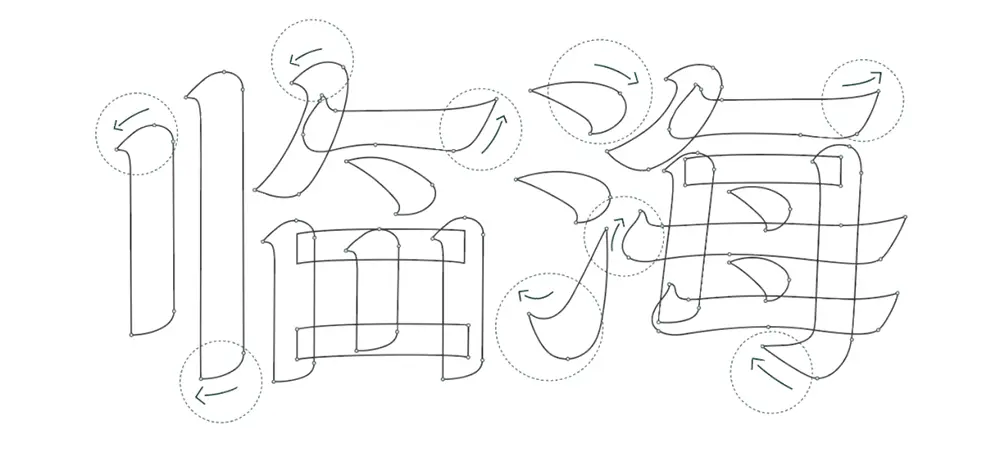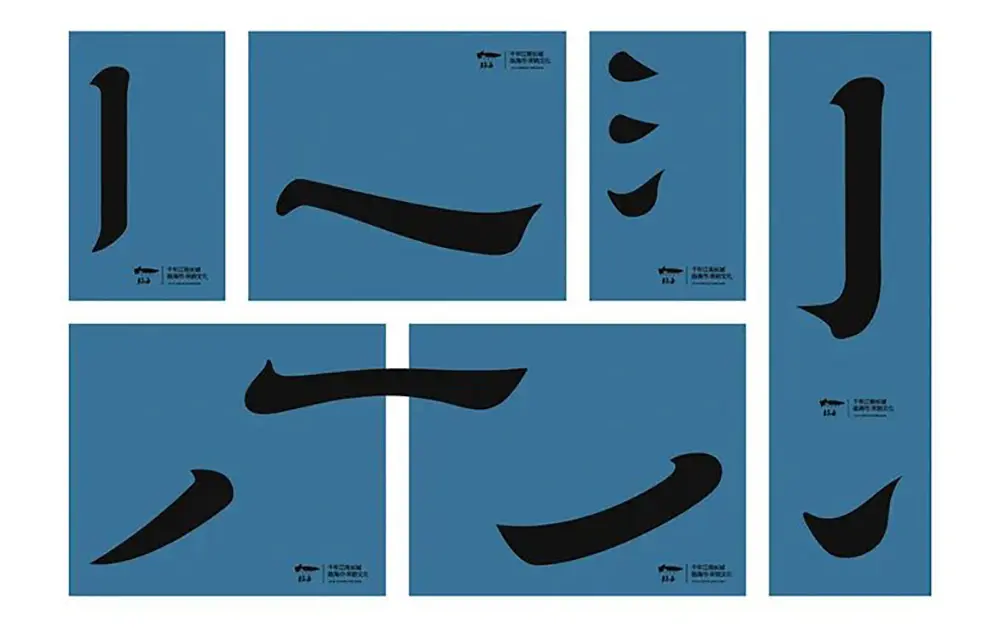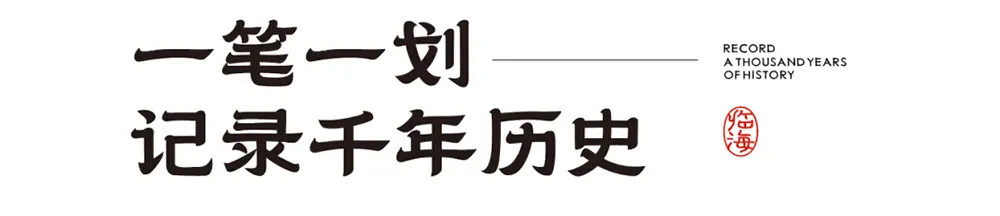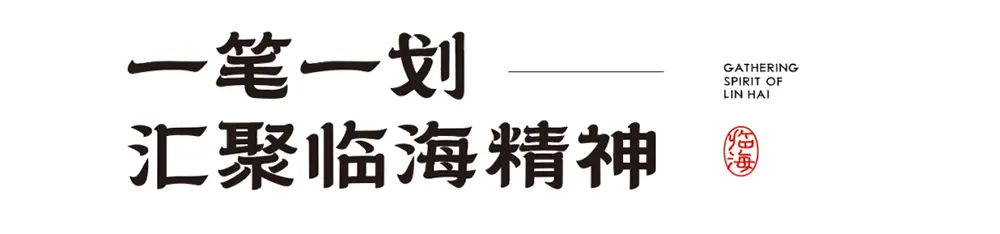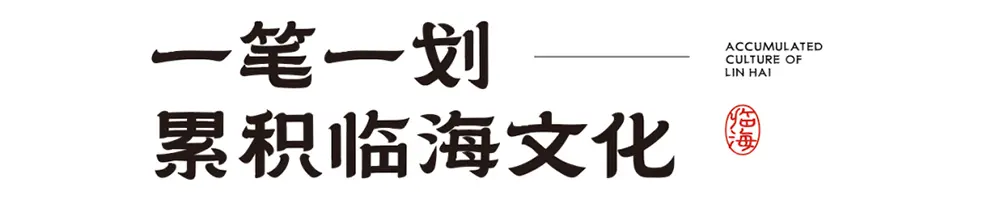
一座城市的影響力取決於城市文化的影響力,經營城市品牌,經營的是一座城市的文化辨識度......,為持續打響“ 千年台州府、江南真宋城 ”文旅品牌形象,讓文化傳播更具辨識度,市社發集團積極謀劃,深度挖掘臨海文化內涵,與鄉立方團隊攜手打造推出了擁有臨海獨特風格和時代烙印的專屬字體。
台州府城牆、龍興寺、千年紫陽街等,文化古蹟星羅棋佈,駱賓王、戚繼光、朱自清等,敘說著臨海文化綿長的故事,文人舞墨,匠者築基,共同鑄就了臨海的文化底蘊,正因如此臨海能較早躋身於“國家歷史文化名城”之列,能有信心對世界說“千年古城,最憶臨海”。
歷史底蘊深厚、文化資源豐富,這是臨海不可複製的獨特稟賦,但如何讓世界認識臨海呢,源浚者流長,根深者葉茂,文字是文化傳承的標誌,臨海字體,更是傳播臨海文化的基礎元素。
一城化一字,一字如一城,站在時光的縱軸上向前望去,隸書的演變史,也是臨海城市變遷的縮影。
將千年古城、人文繁盛、山水之韻,等臨海城市特質,結合漢字五大字體之一的隸書體,隸書,興盛於漢代,也是臨海城市起源的時代,隸書所具有的厚重、古典、拙樸特質,曠達雄渾,古樸內斂,將臨海的城市特質展示的淋漓盡致。
臨海古城,也就是台州府城,始建於晉,擴建於唐,距今已有1600多年的歷史。古城原有七門十三敵臺,現僅存四門和四座敵臺。
江南長城,是江南地區唯一的長城,城牆依山就勢,俯視大江,敵樓林立,氣勢恢宏,是北方明長城的師範和藍本,人稱“江南八達嶺”,現存近5000米,目前已列入世界文化遺產預備名單之中。
紫陽古街,全長1080米,是整個古城的中軸線,有“臨海第一古街之稱”,街道兩邊的房屋店鋪雕樑畫棟、古色古香,保留著宋代遺風、明清格局。
在這裡,戚繼光馳騁海疆“封侯非我意,但願海波平”。在這裡,駱賓王仗劍而起“寶劍思存楚,金錘許報韓”。“莫言滄海闊,杯度自應知”,最澄大師萬里求法,化成千佛塔的“菩薩垂眉,萬千悲憫”。
無論是臨海詞調、黃沙獅子、大石車燈、大田板龍、小芝鼓亭、上盤花鼓、城關細吹亭等傳統民間文化藝術,還是糟羹、麥油脂、馬蹄酥、羊腳蹄、麥餅、蛋清羊尾等傳統風味小吃,亦或是刺繡、草編、竹木雕刻等傳統工藝。
府城人民的智慧,凝結於千家萬戶的煙火之中,彙集成千年臨海的獨特畫卷。
通過臨海字體打造臨海符號化IP,將臨海字體融入到城市的歷史、文化、形象、資源、產品、內容等各個層面,讓臨海字體成為這座城市具有獨特辨識度和人格化的城市品牌。